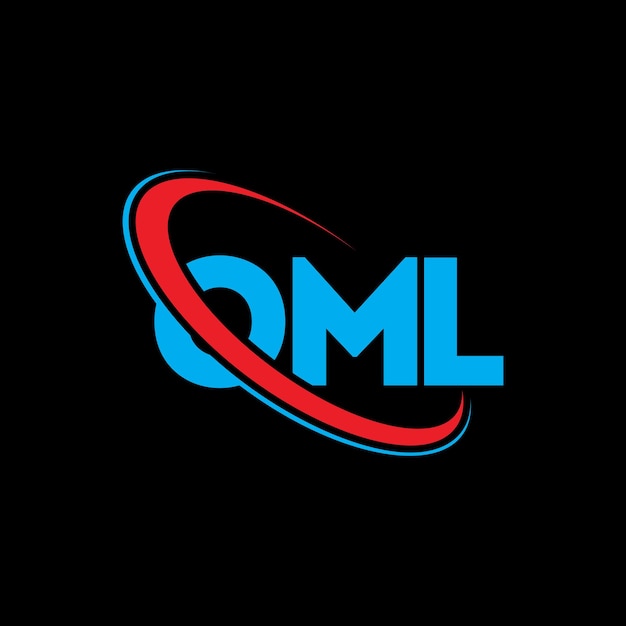
Le logo QML est une lettre QML, une initiale QML liée à un cercle et à une lettre majuscule, un logo QML et une typographie QML pour les entreprises technologiques et les marques immobilières.